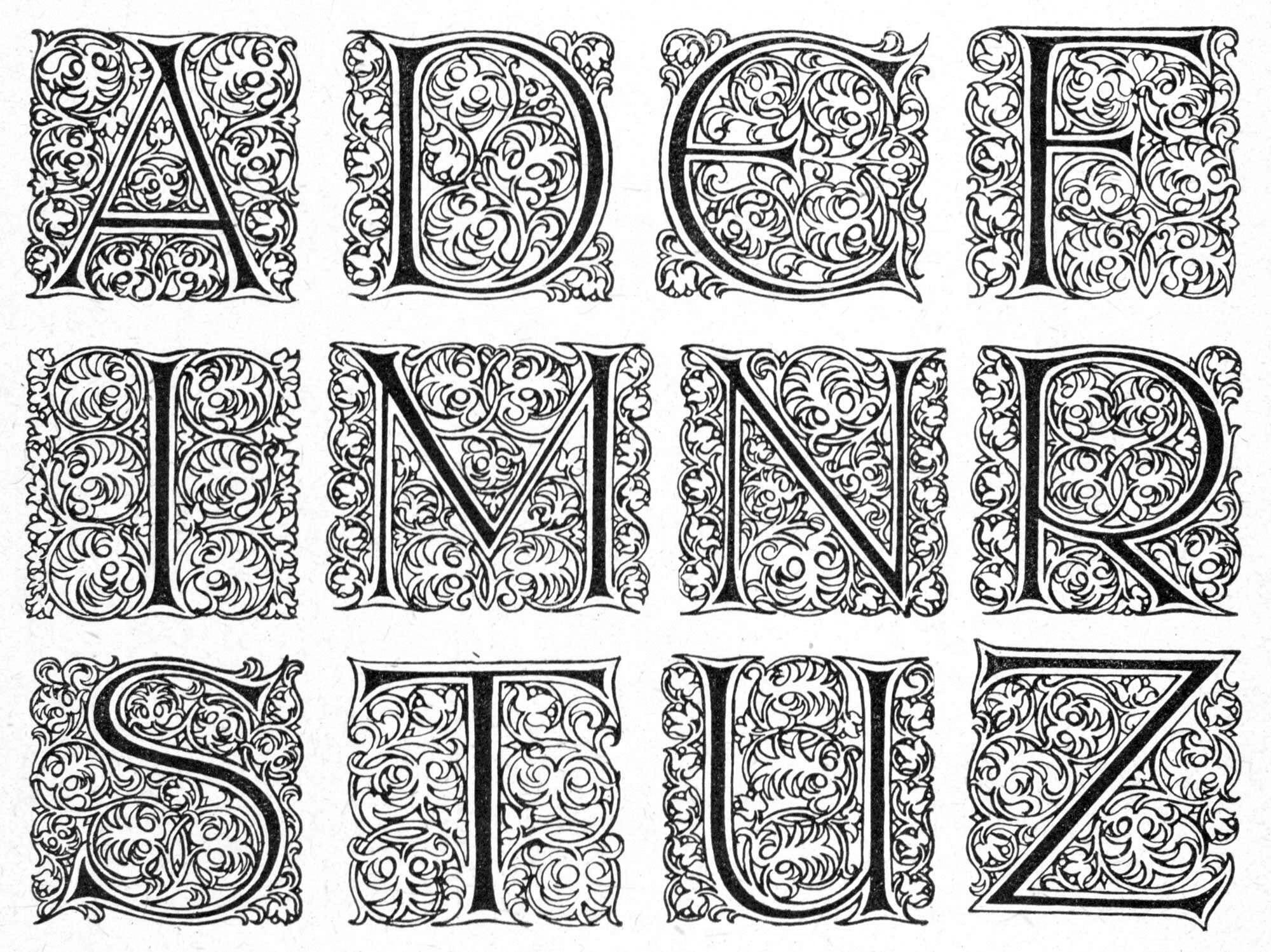
- circa 1916
- Antiqua humanistisch
Die Gotische Antiqua von Friedrich Wilhelm Kleukens erschien in den 1910er-Jahren bei der Schriftgießerei D. Stempel AG. Die Schrift in einem Schnitt verbindet Elemente verschiedener Schriftgattungen: Im Buchstabenskelett dominieren Antiqua-Formen. Die Strichführung enthält Elemente gebrochener Schriften. Und für einige Großbuchstaben waren alternative Unzialformen erhältlich. Zusätzlich erhältlich waren Initialen.
Digitalisierungen sind nicht bekannt.